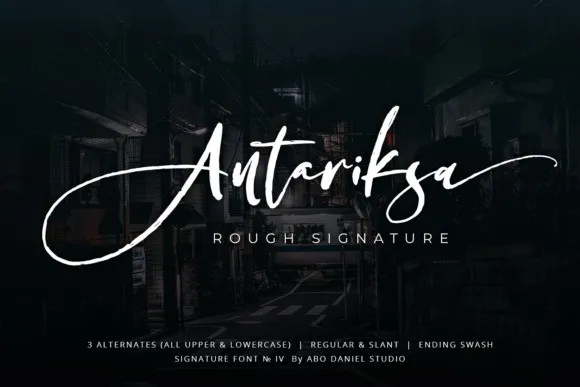
Antariksa Script Font – Fonte Grátis
Antariksa Script Font
A Antariksa Script Font é uma escolha perfeita para quem deseja dar um toque elegante e moderno a seus projetos digitais. Com seu estilo natural e sua aparência feita à mão com caneta, ela oferece uma variedade de opções únicas que podem ser usadas em diferentes ambientes de design. Desenvolvida especialmente para aqueles buscando um ar refinado e contemporâneo em suas criações, esta fonte é o ideal para designers digitais de todos os níveis. Com linhas ricas e uma textura sofisticada, a Antariksa Calligraphy Script permite que seus projetos ganhem vida através dos mais variados métodos de impressão. Seja criando um design meticuloso para tecelagem, laser corte, costura Cricut ou mesmo adicionar um toque de metal líquido, a Antariksa pode ser usada em praticamente qualquer tecnica de impressão existente. Além disso, o seu recurso de desenho regular e inclinado permite criar uma diversidade impressionante de resultados, tornando-a ideal para designers experientes e iniciantes que buscam dar um toque único a seus projetos.